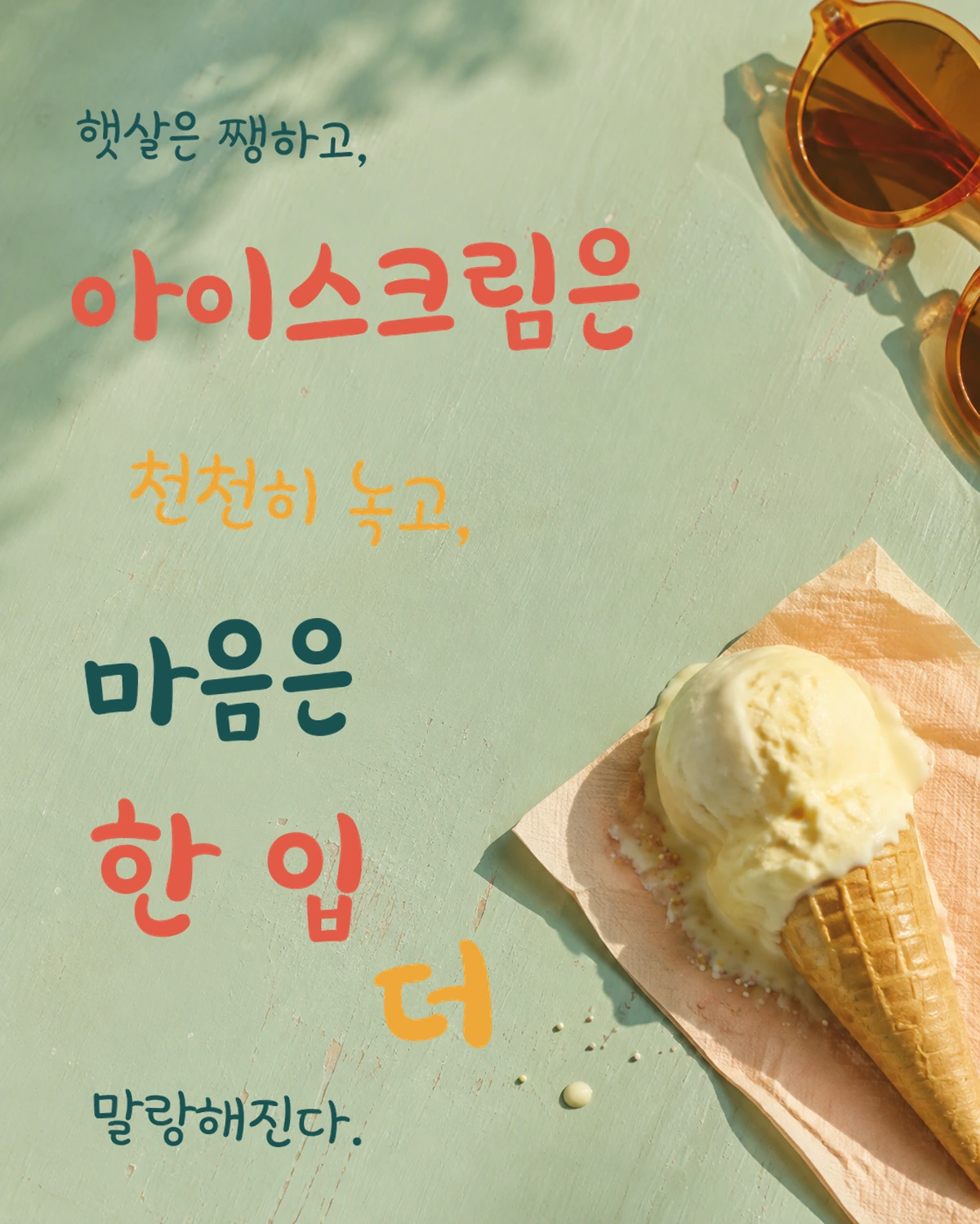
빙그레싸만코체 — 빙그레에서 배포하는 무료 폰트입니다. 붕어싸만코의 붕어 모양을 옮겨 통통하게 부푼 획으로 그린, 달콤하고 유쾌한 인상의 손글씨체
빙그레 한글서체 시리즈의 다섯 번째 작품으로 2020년에 윤디자인그룹과 함께 만들었습니다. 모티브는 이름 그대로 붕어싸만코인데, 여기서 흔히 오해가 생깁니다. 모나카 과자가 아니라 붕어 모양입니다. 제작사도 친숙한 붕어 과자에 달콤한 통팥 시럽을 가득 담은 붕어싸만코를 서체로 옮겼다고 밝히고 있고, 붕어 형상을 담은 딩벳도 함께 들어 있습니다.
같은 회사의 빙그레체가 둥근 고딕 계열이라면 이쪽은 손글씨입니다. 제작사는 손글씨 특유의 자연스러움을 느낄 수 있다고 설명하면서, 두 굵기의 성격을 이렇게 나눕니다. Bold는 두꺼운 붓으로 쓴 자연스러움을, Regular는 가는 사인펜으로 또박또박 쓴 정갈함을 표현했다는 것입니다.